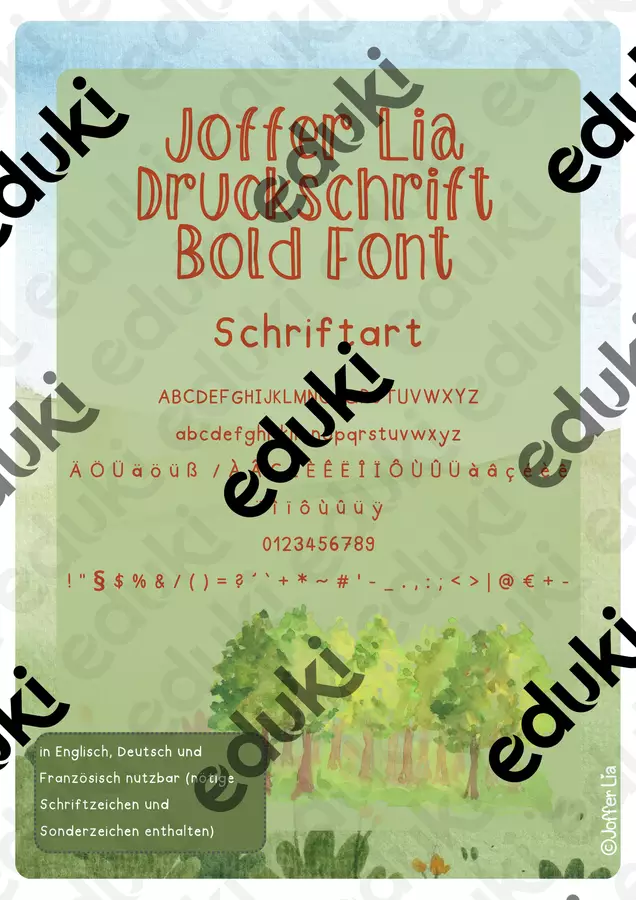
Du suchst eine klare und ansprechende Schriftart für deine Unterrichtsmaterialien? Dann ist die "Joffer Lia Druckschrift Bold Font" genau das Richtige für dich!
• Eine gut lesbare Druckschrift in kräftigem Bold-Stil, die sofort ins Auge fällt.
• Volle Unterstützung für Deutsch, Englisch und Französisch, inklusive aller nötigen Sonderzeichen wie Ä, Ö, Ü, ß, À, Ç, É, È, Ê, Ë, Î, Ï, Ô, Ù, Û, Ü, Ÿ.
• Alle Groß- und Kleinbuchstaben, Zahlen und gängigen Satzzeichen sind enthalten, damit du flexibel arbeiten kannst.